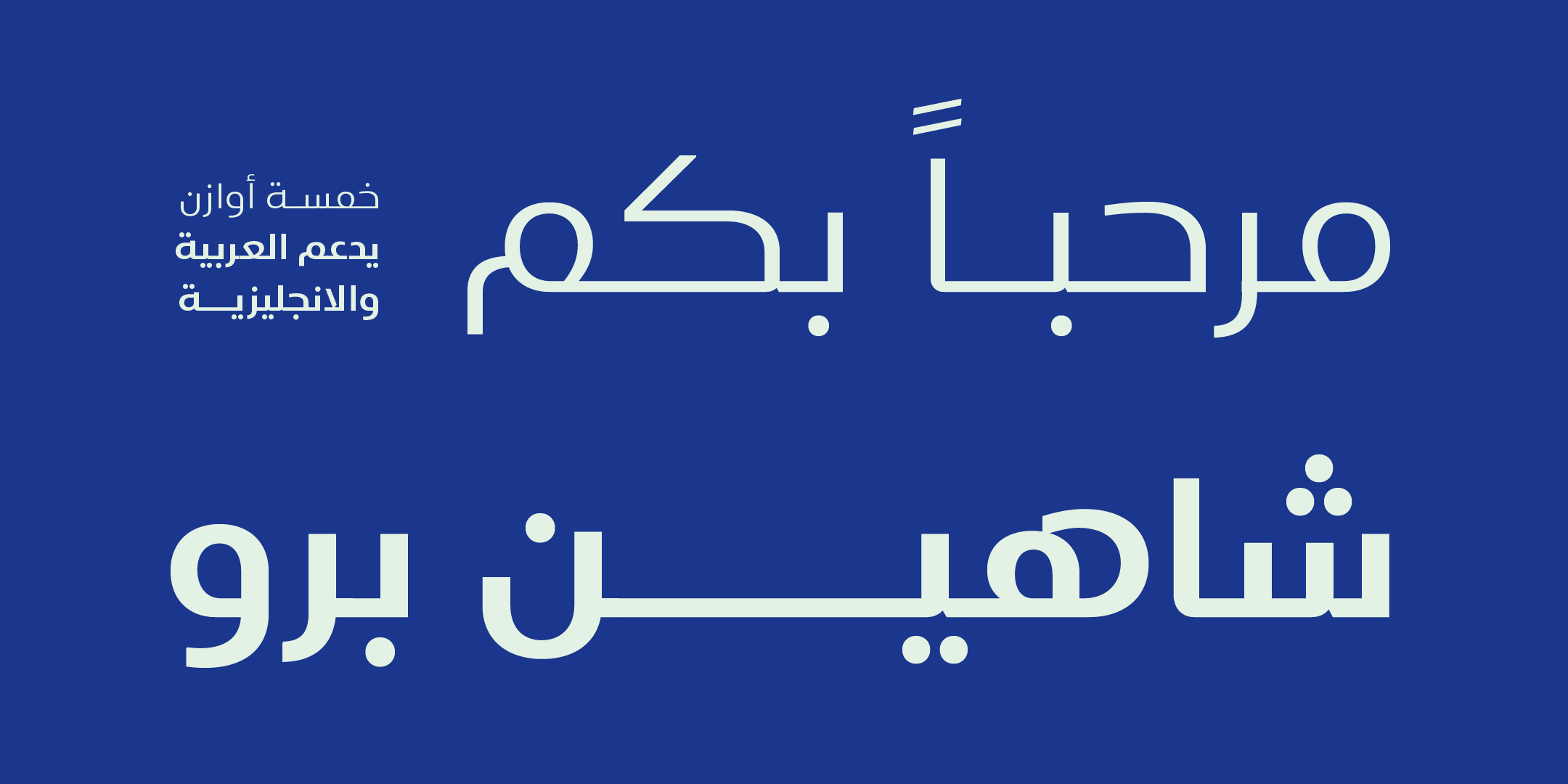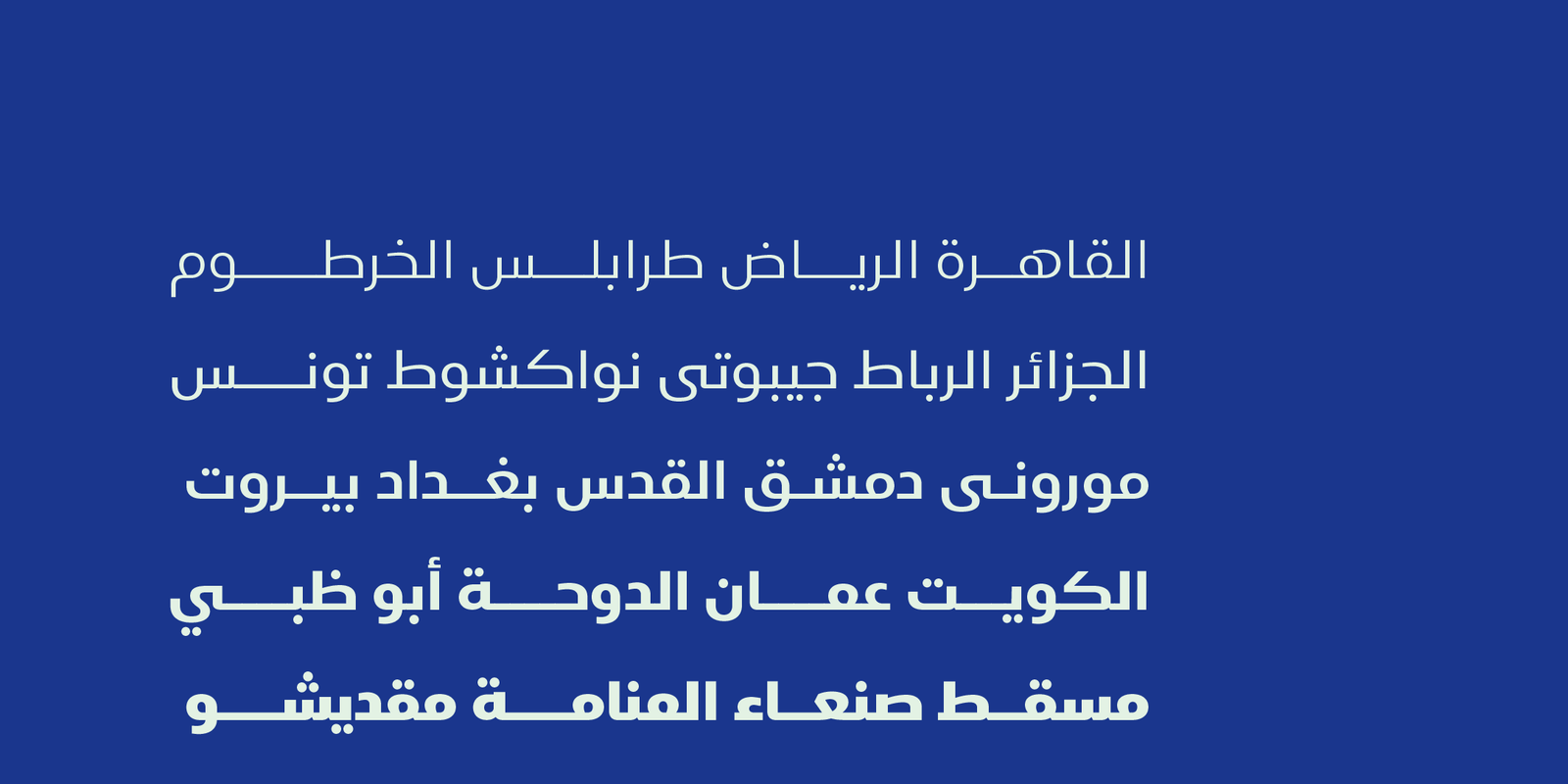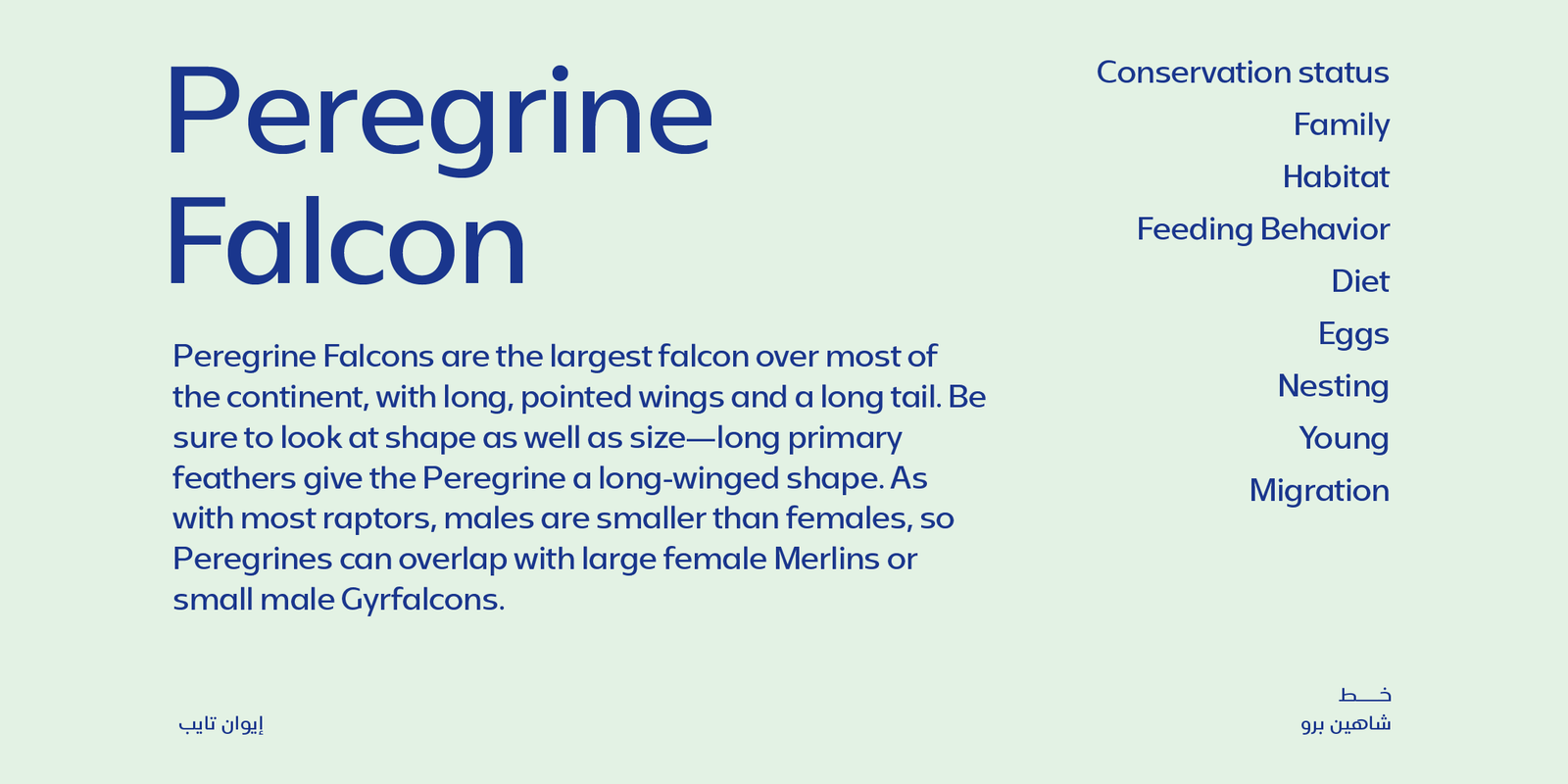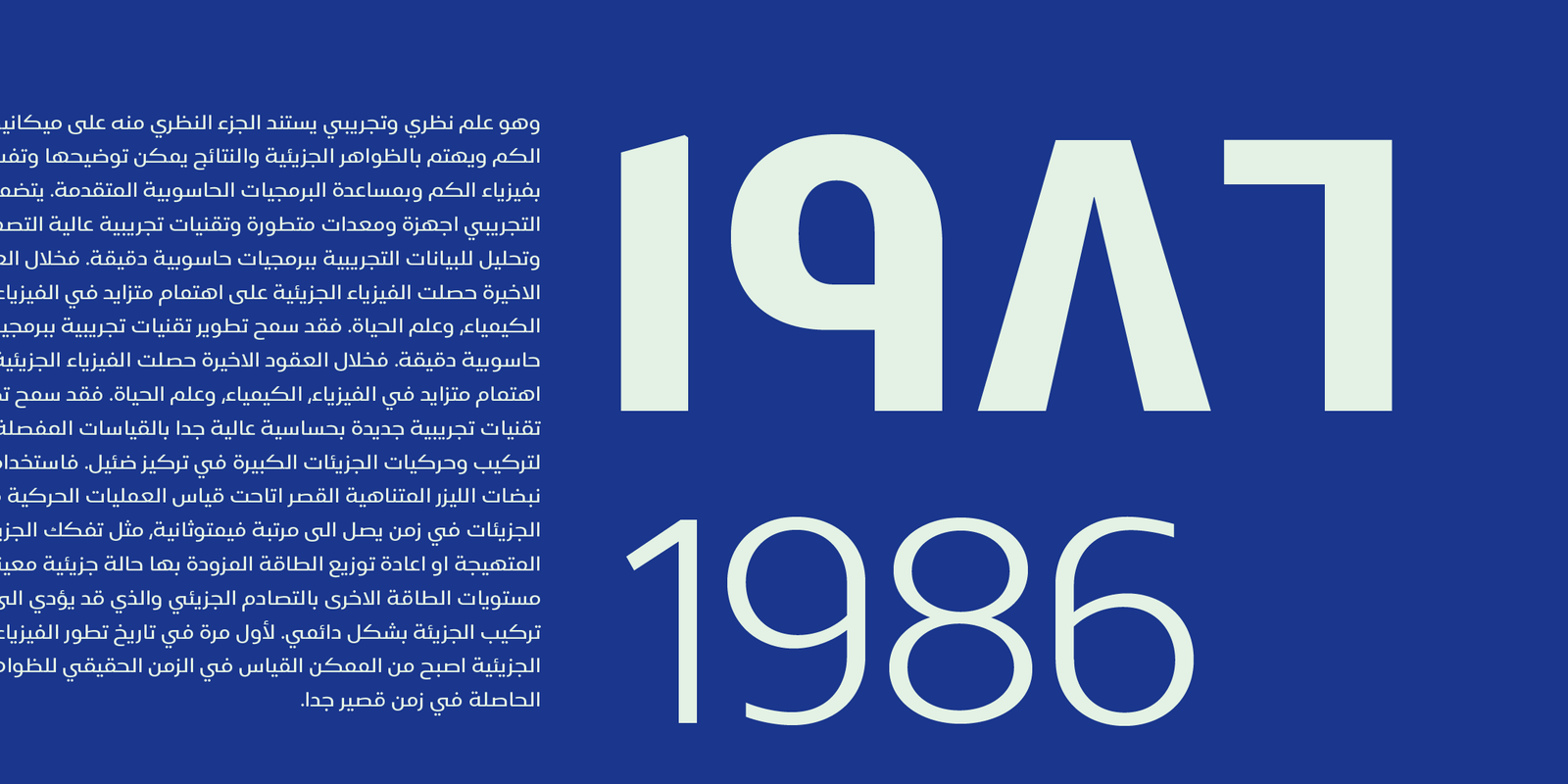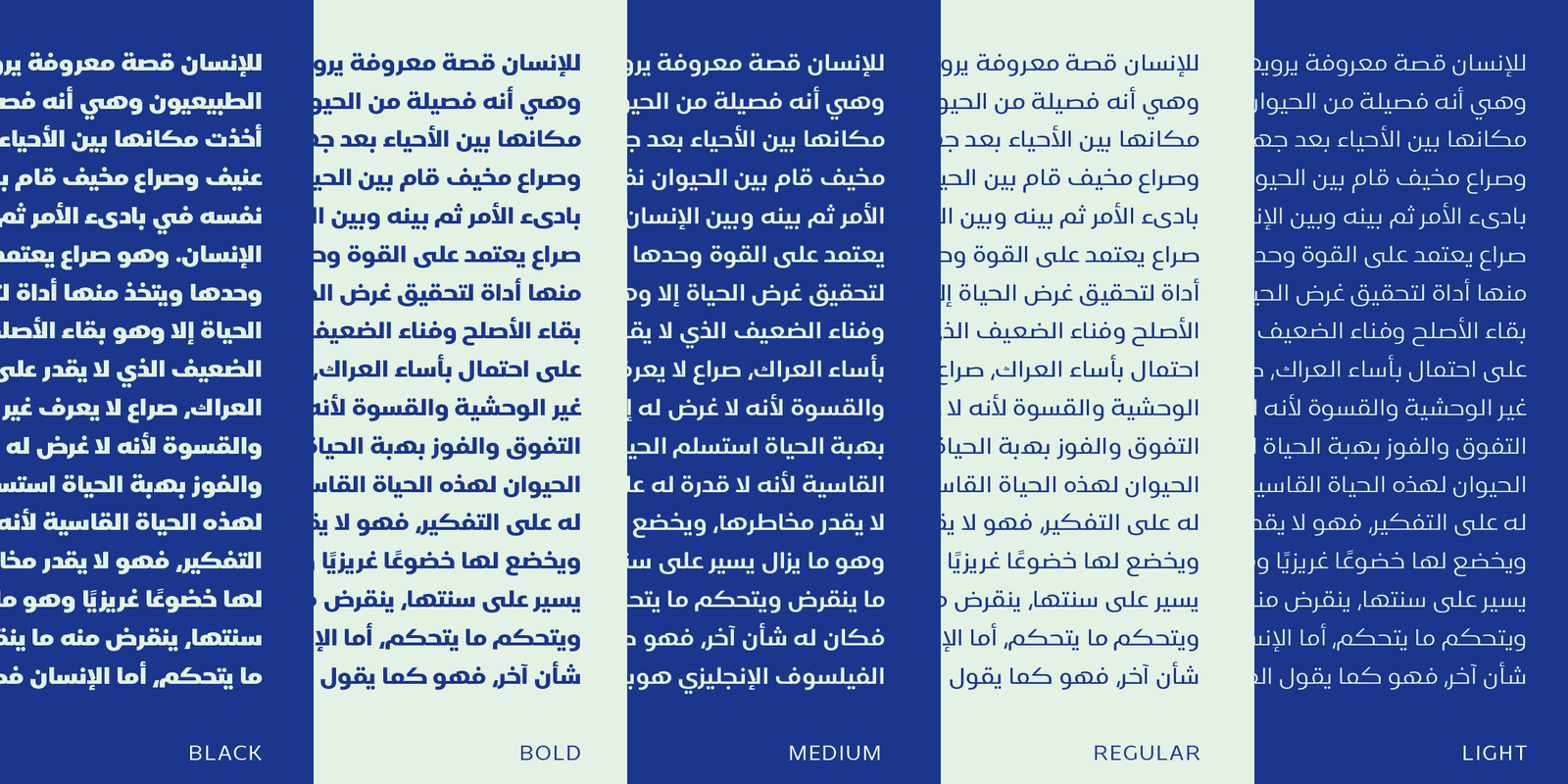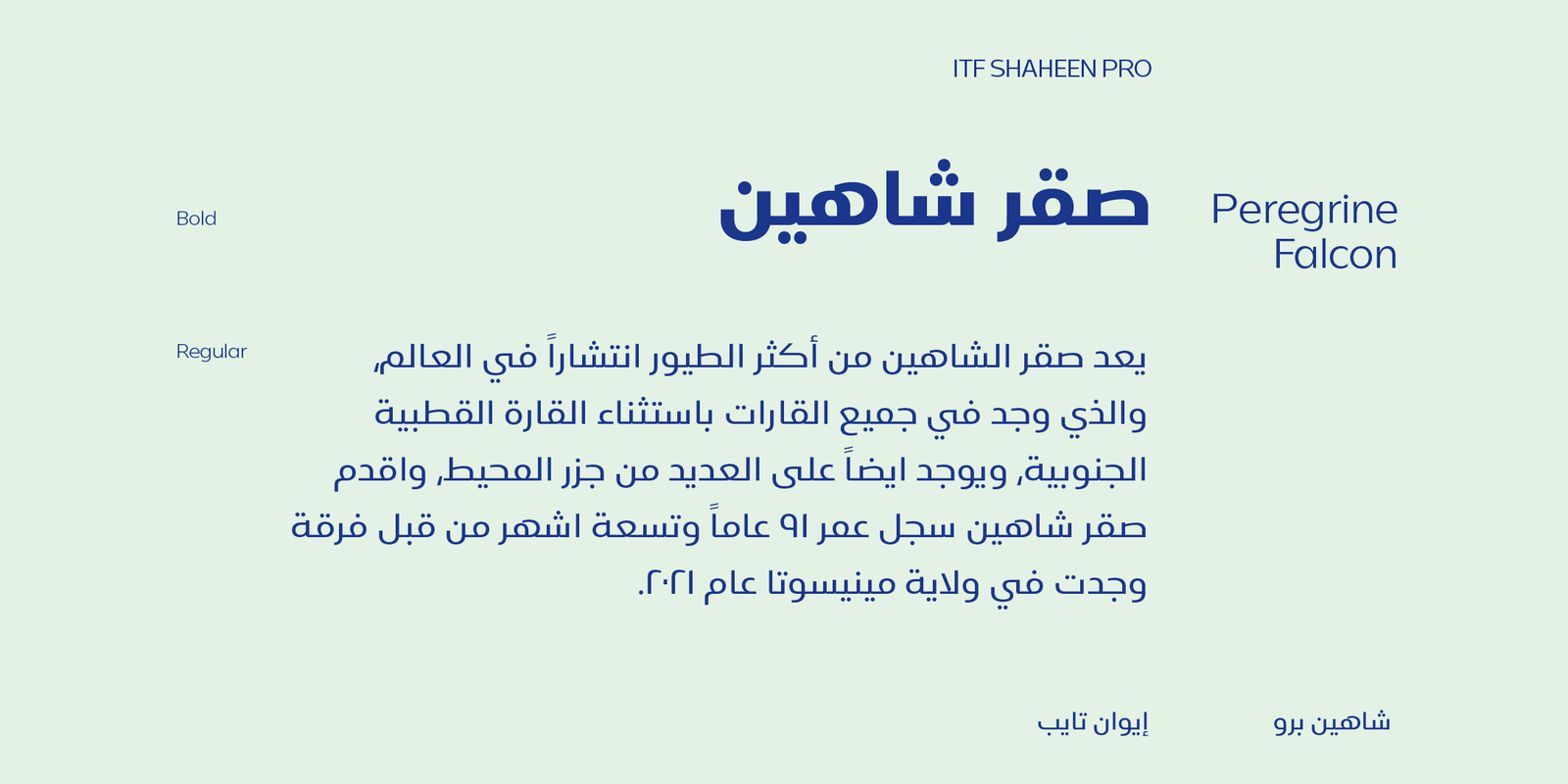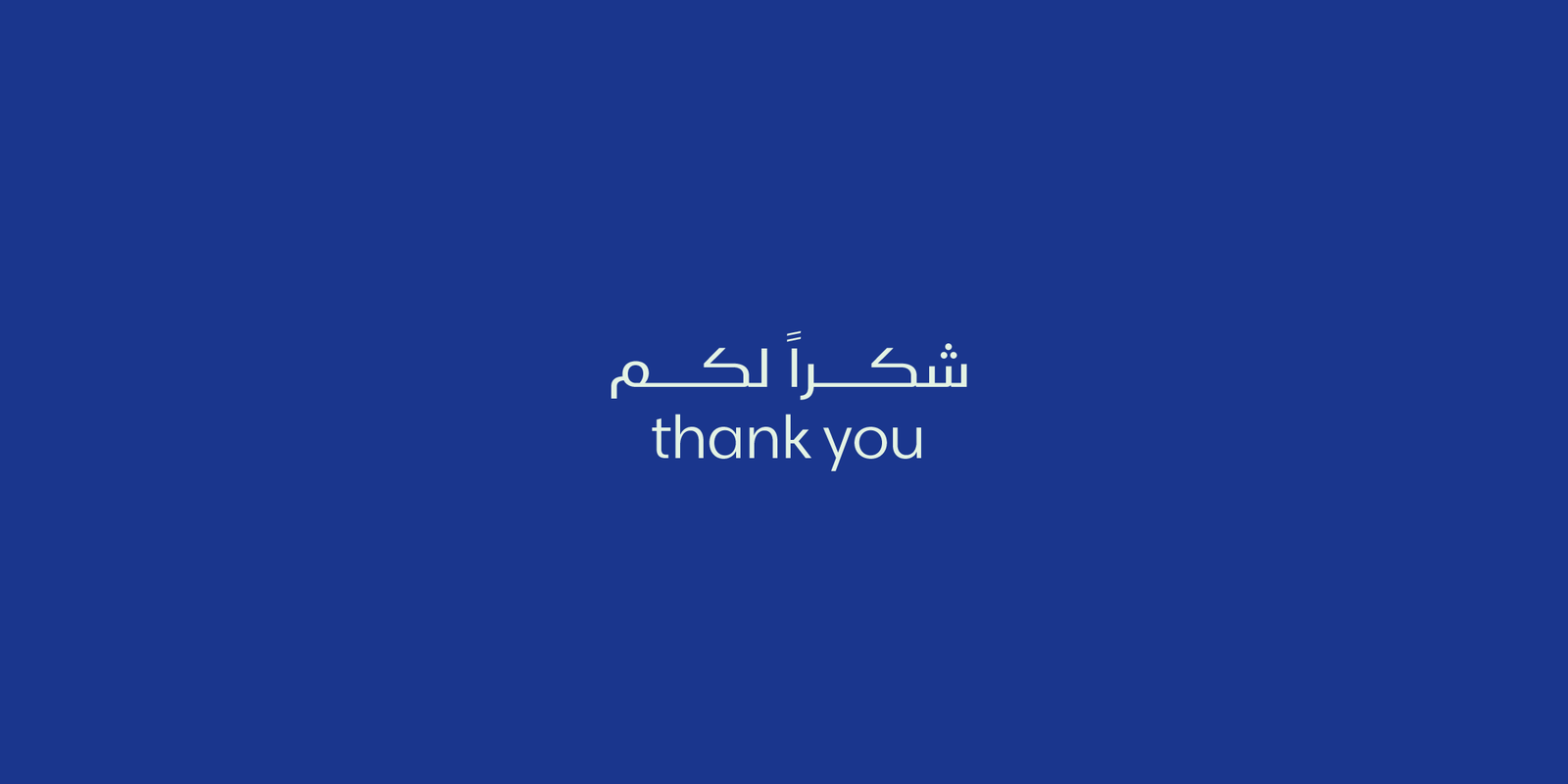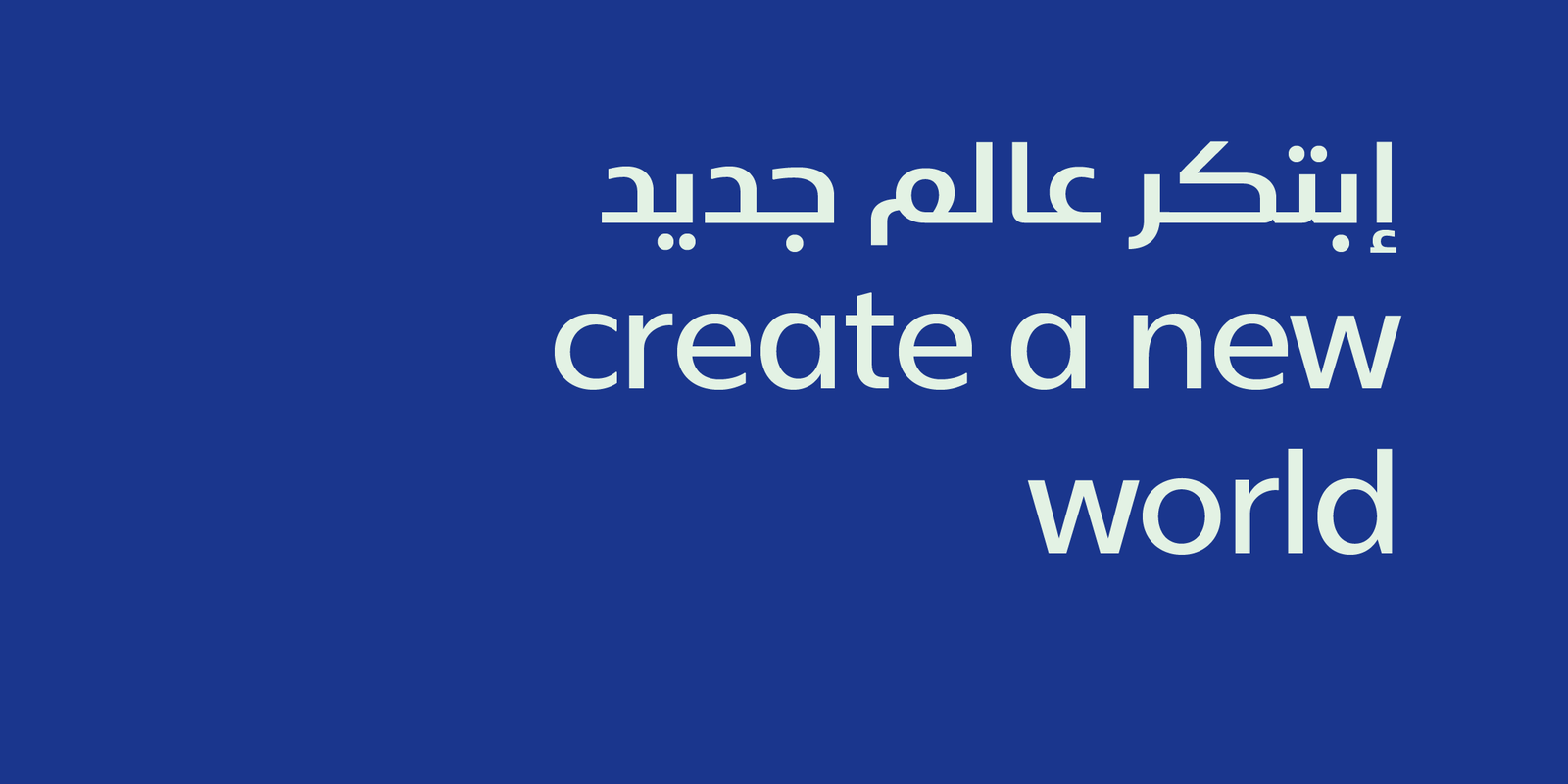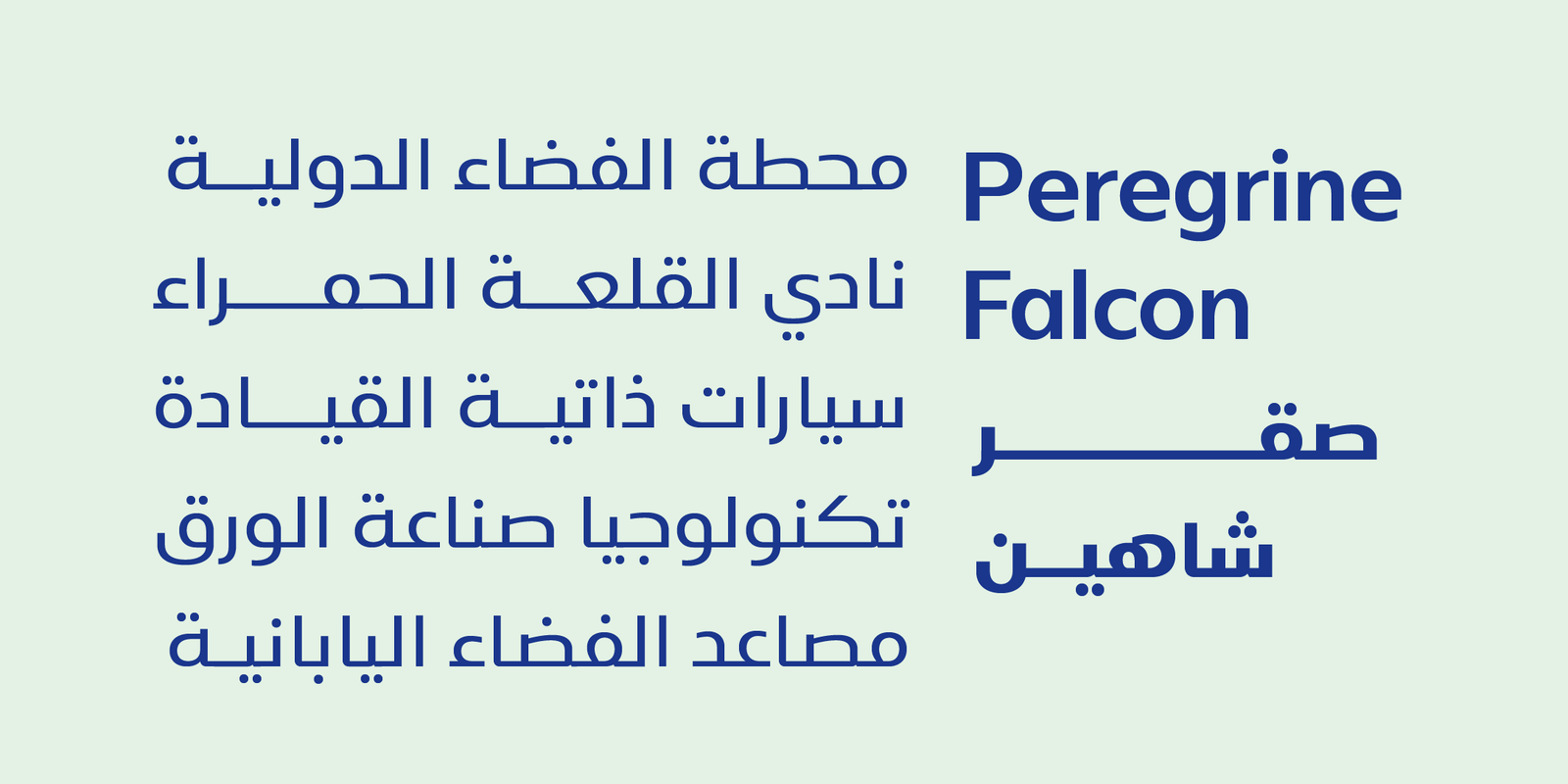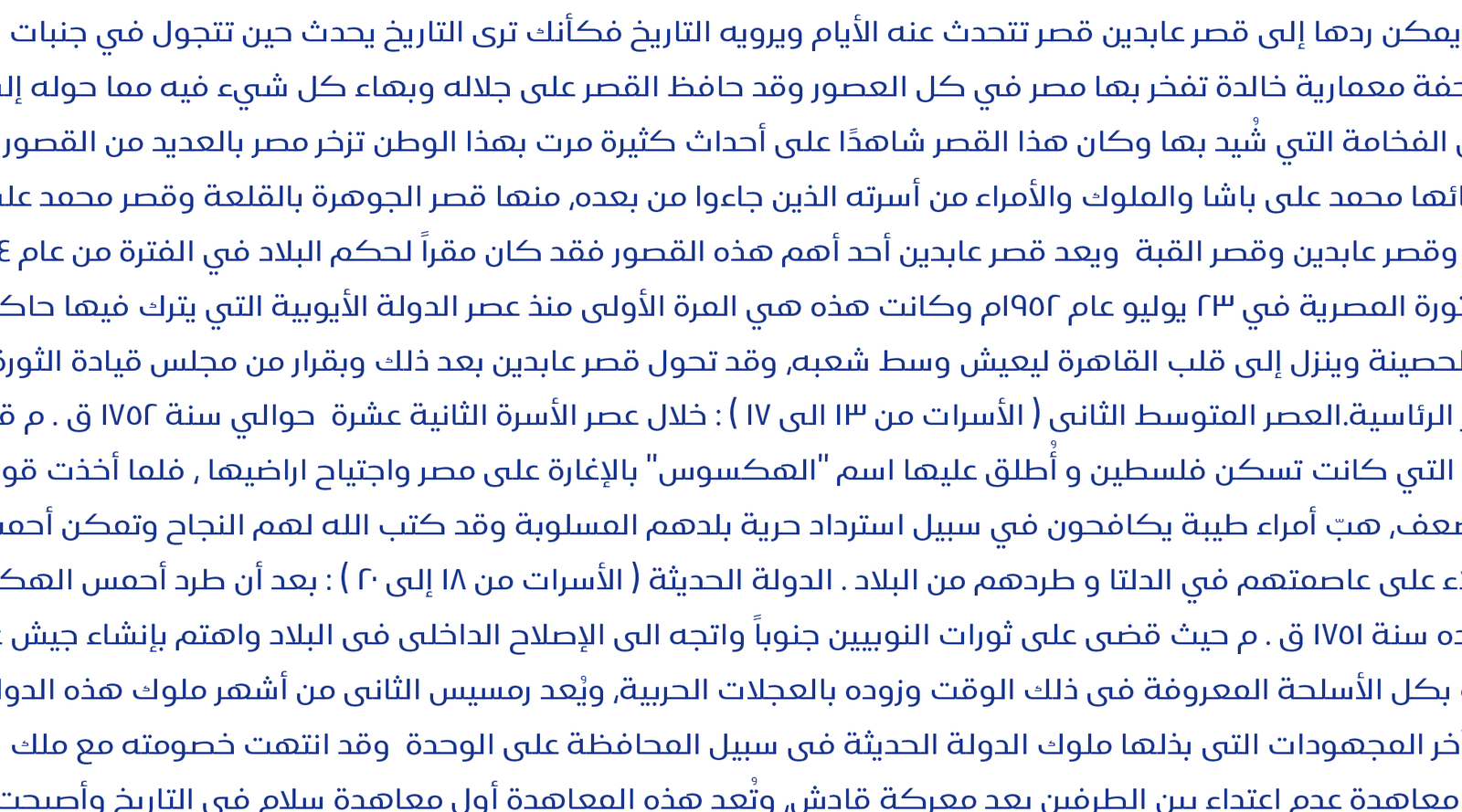
خط شاهين برو – Shaheen pro Arabic typeface
Shaheen pro is a version of Shaheen typeface, Shaheen pro is an Arabic and Latin typeface that embodies power and a tendency towards uniformity. While preserving the neat, minimalist look which is associated with it. The name, too, hints at the strong character of the typeface. Shaheen pro comes in 5 weights
شاهين برو هو اصدار ثاني من خط شاهين و هو خط عربي وانجليزي يجسد القوة والميل نحو الوحدة. مع الحفاظ على المظهر الأنيق والبسيط المرتبط به. يشير الاسم أيضًا إلى الطابع القوي للخط. شاهين برو يأتي في 5 أوزان
اللغات: العربية والانجليزية
الاوزان : خمسة أوزان